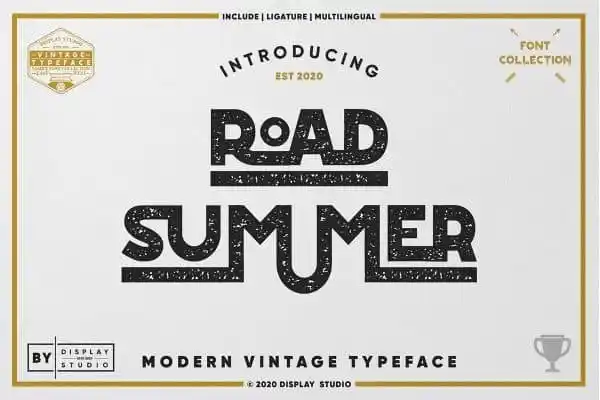
Road Summer Display Font – Fonte Grátis
Road Summer Display Font
A fonte ‘Road Summer Display Font’ é uma tipografia limpa e desbotada que oferece um enfoque angulado aos caracteres. Suas formas simples mas limpas são perfeitas para uso tanto como texto de corpo quanto como tipo-display. Esta fonte é ideal para projetos de identidade corporativa, logotipos, capas de livros, designs de camisetas, posts no social media, anúncios, embalagens de produtos, design dos produtos, etiquetas, marcas d’água, convites e cartões de visita. É uma opção perfeita para qualquer projeto que exija um estilo atraente e moderno, capaz de destacar sua visão única.